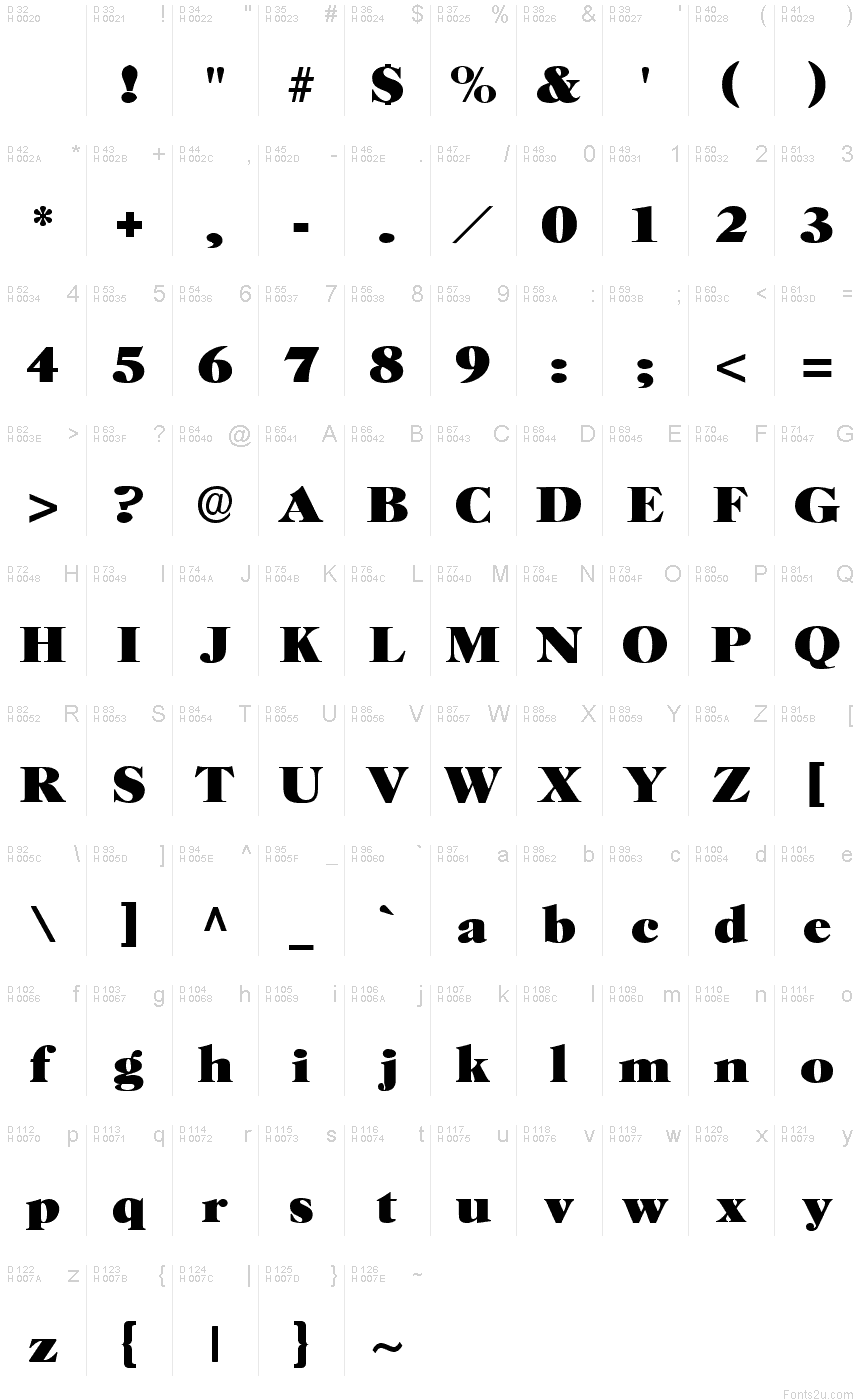
Broadview to darmowy krój szeryfowy o śmiałej, niemal teatralnej prezencji, która natychmiast przyciąga wzrok. Masywne szeryfy i zwarte formy nadają każdemu słowu solidny, „tuszu” charakter, sprawiając, że nagłówki wyglądają pewnie i wyraziście, nie tracąc przy tym lekkości. Jej vintage’owy klimat przejawia się w zaokrąglonych łukach i solidnych kształtach, które dodają ciepła nawet prostym kompozycjom.
Ten darmowy font świetnie sprawdza się na plakatach, okładkach książek, w tytułach redakcyjnych, logotypach, na opakowaniach i wyrazistych grafikach do mediów społecznościowych, gdzie liczy się mocne pierwsze wrażenie. Stosowanie Broadview w większych rozmiarach pozwala jej gęstym formom „odetchnąć”, a zestawienie jej z prostym bezszeryfowym krojem w tekście głównym zapewnia czytelność i równowagę. Duża waga liter naturalnie buduje hierarchię, dzięki czemu nawet minimalistyczne projekty wyglądają na kompletne przy użyciu zaledwie kilku dobrze ustawionych słów.